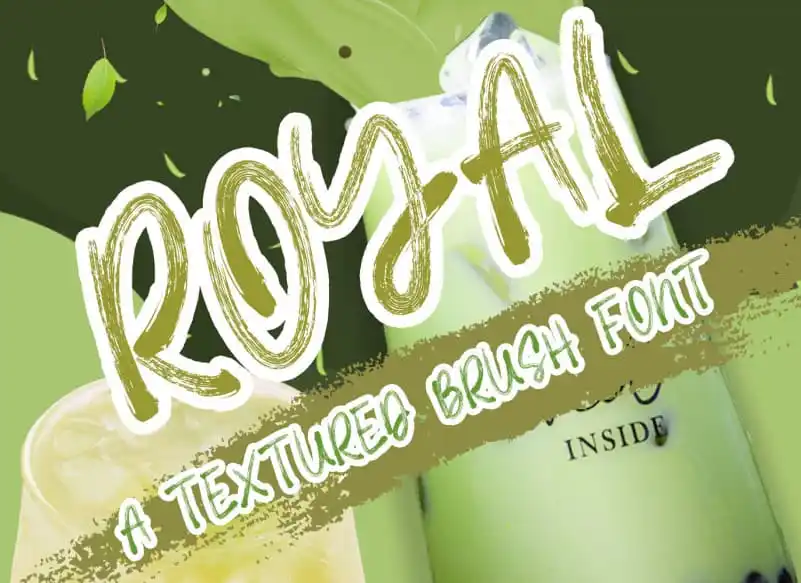
A Royal Brush Font é uma escolha perfeita para quem busca uma fonte de script que transborda vida e energia. Ela se assemelha a uma escrita a mão feita rapidamente, mas também incorpora detalhes aguçados e movimentos rápidos, criando um efeito vibrante e intrigante. Com 177Studio como seu designer, esta fonte é projetada para dar vida às suas mensagens mais pessoais ou artísticas. Seja você uma autora de blogs inspiradoras, uma redatora criativa ou mesmo um estilista de moda que busca um toque único em seus designs, a Royal Brush Font trará uma aparição poderosa e vibrante ao seu trabalho. A sua versão script é perfeitamente adaptada para o design de letras largas, fazendo-a uma opção irresistível para personalizar qualquer projeto.